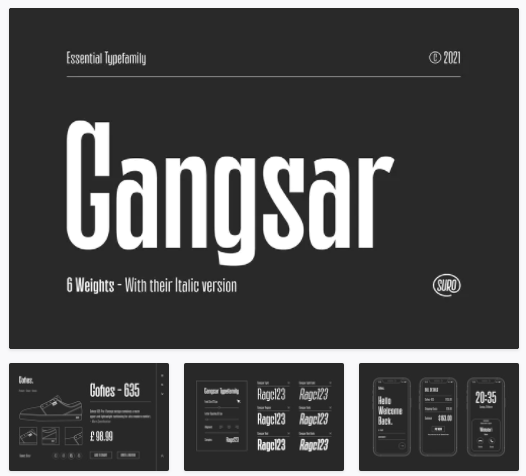
Gangsar - это конденсированный шрифт, вдохновленный шрифтом Enge Hermes (1935).
Имеет 6 начертаний, включая курсив, сильный характер, острые края и пропорциональный контраст.
Шрифт универсален и может быть успешно использован в брендинге, плакатах, журналах, веб-сайтах, мобильных приложениях и т.д.